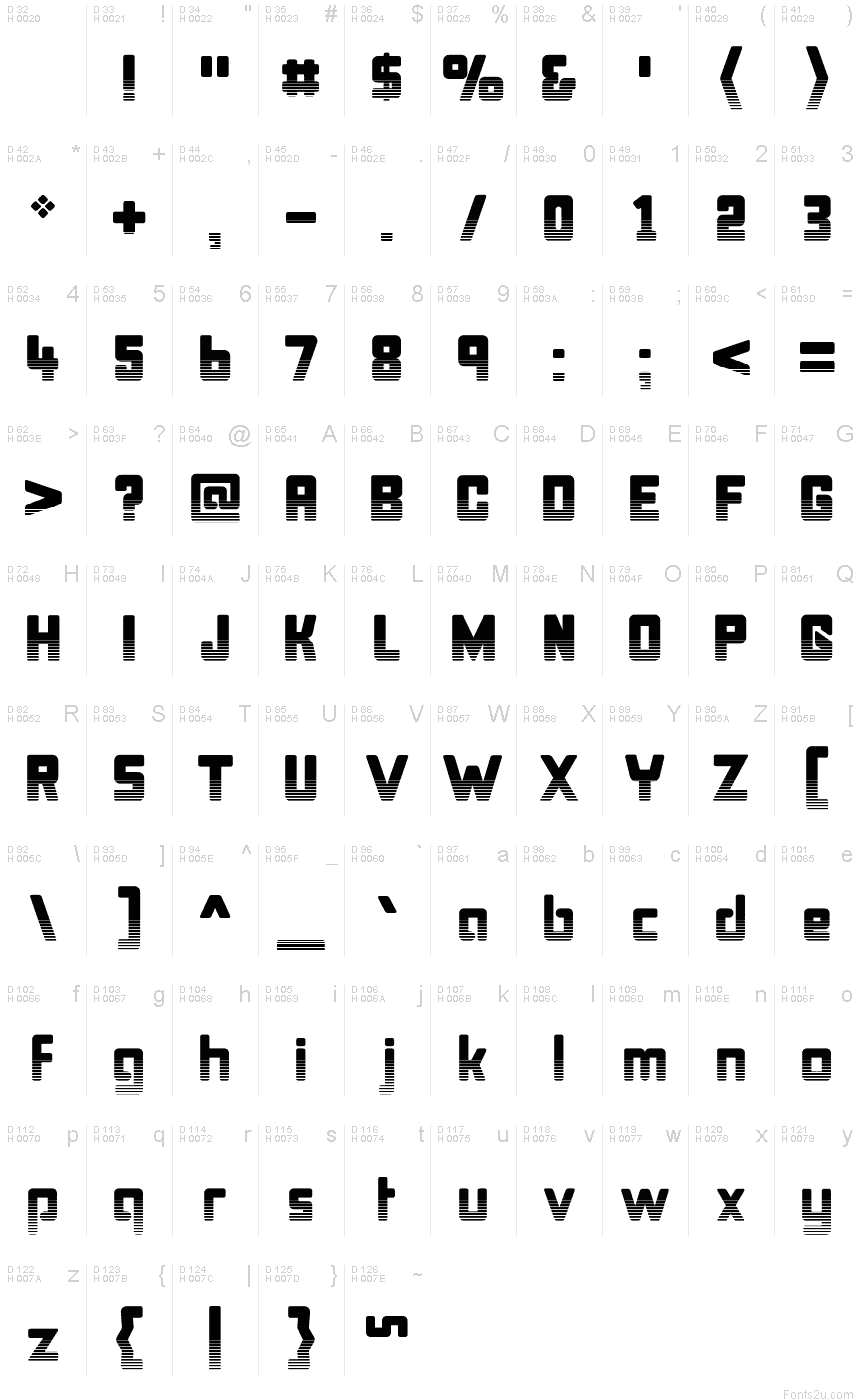
Bonk Undercut od GemFonts to darmowy, retro font typu display. Jego kanciaste, masywne kształty przypominają liternictwo z gier arcade wycięte w czarnym plastiku, a cienkie, poziome linie „undercut” dodają dynamicznego rytmu, przywodzącego na myśl szybkość i poświatę starych monitorów CRT. Mimo swojej wyrazistości, dzięki kreskowaniu, krój nie wydaje się zbyt ciężki.
Bonk Undercut świetnie sprawdzi się w logotypach gier, plakatach sci-fi, ulotkach technologicznych, nagłówkach e-sportowych, projektach naklejek, grafikach na okładki albumów i przyciągających wzrok miniaturach na YouTube. Stosuj Bonk Undercut w dużym rozmiarze, aby linie były czytelne, i zestaw go z prostym, geometrycznym fontem bezszeryfowym w tekście głównym, pozwalając temu darmowemu krojowi grać pierwsze skrzypce.